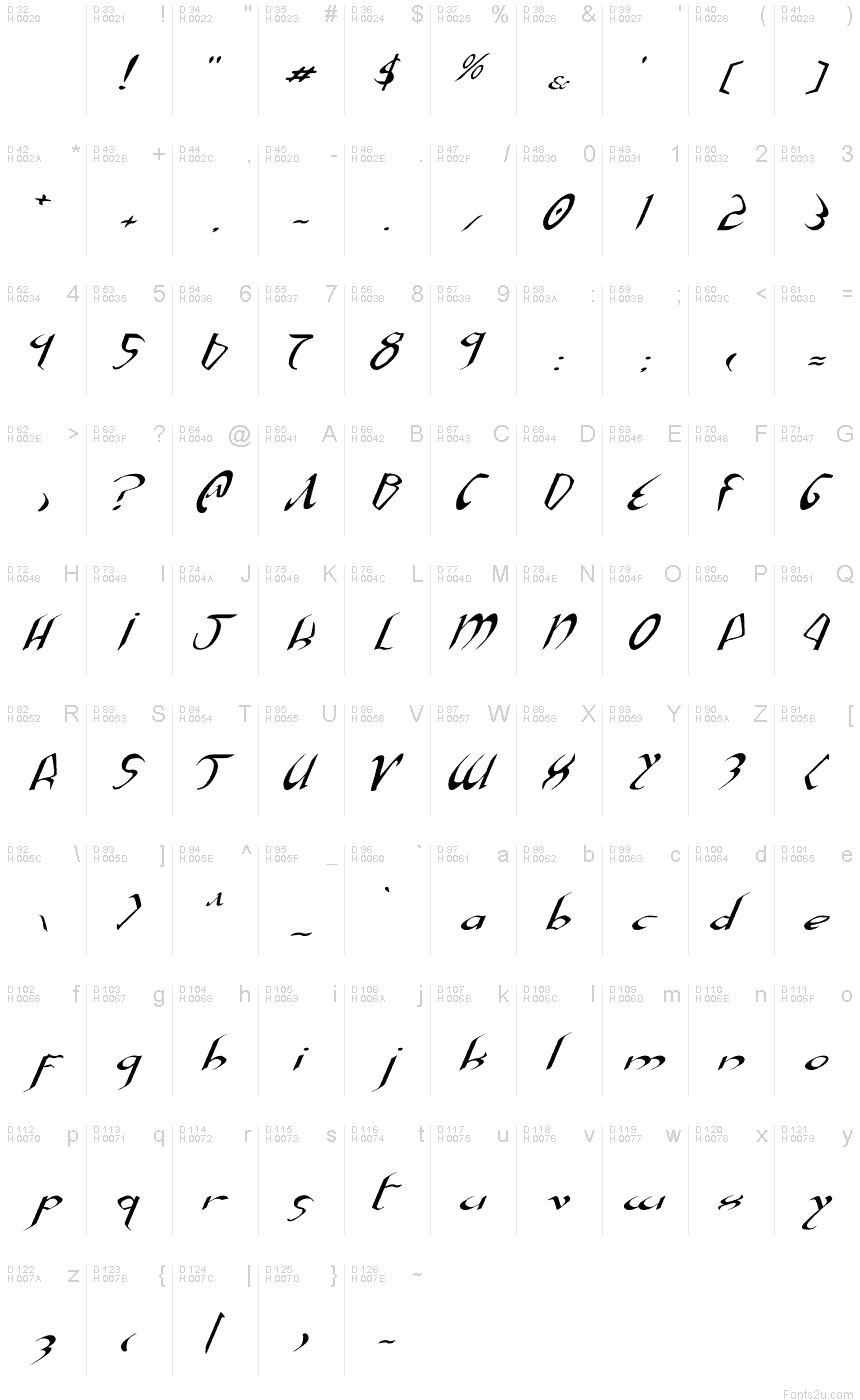
Xaphan Expanded Italic to darmowy, kaligraficzny krój pisma odręcznego od Iconian Fonts z 2003 roku, który mocno osadzony jest w klimacie dark fantasy. Litery wyciągają się w przód długimi, przypominającymi ostrza pociągnięciami i zahaczonymi łukami, łącząc kaligraficzny rytm z ostrymi, niemal piekielnymi kształtami, co nadaje całości napięcia i teatralnego wyrazu.
Ten darmowy font świetnie sprawdzi się na metalowych ulotkach, plakatach horrorów, logotypach gier, okładkach książek o tematyce okultystycznej oraz tytułach, które potrzebują rytualnego, drapieżnego charakteru. Dzięki mocnemu pochyleniu i kolczastym krzywiznom, nawet krótkie słowa czy monogramy zyskują w nim dynamikę.